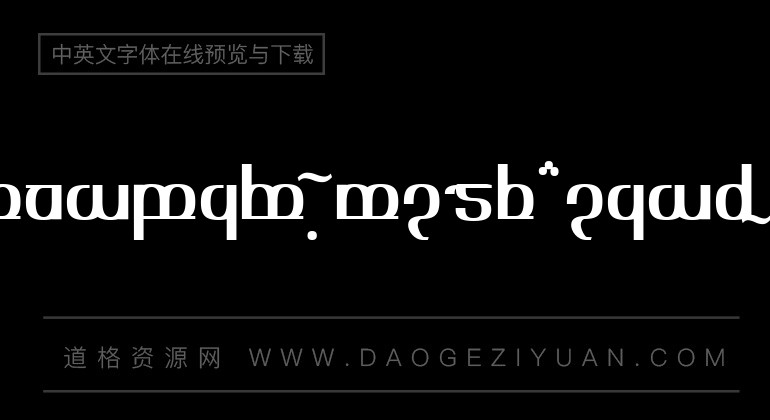
Tengwar Optime Diagon 是一款基于Tengwar字体的开源字体,由Juan Jose Marcos提供。它是一款精美的Tengwar字体,具有精细的线条,清晰的外观,可以在任何地方使用。它可以用于创建精美的文本,也可以用于制作图标,广告,图形设计等等。它还可以用于创建原创的Tengwar文字,用于创作各种故事,文章,书籍等等。内容介绍
Tengwar Optime Diagon是一款非常不错的手写艺术字体,具有很好的视觉感,适合于文化类的宣传设计、商业类品牌的广告和产品包装设计以及个性化文字排版等较多场景。